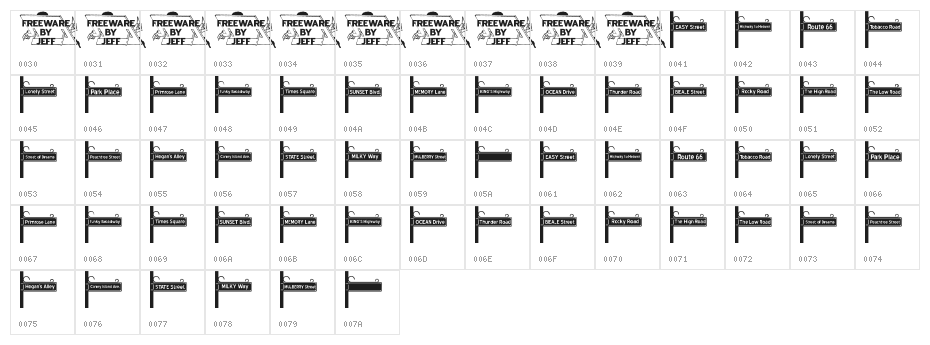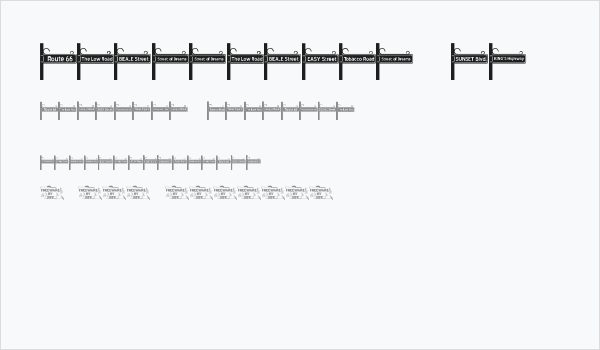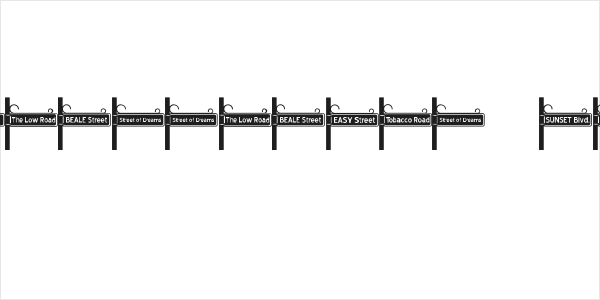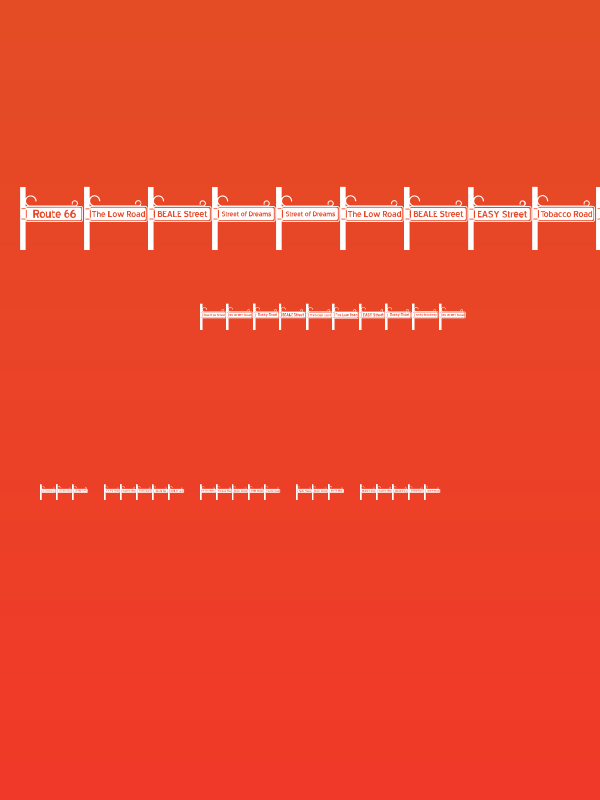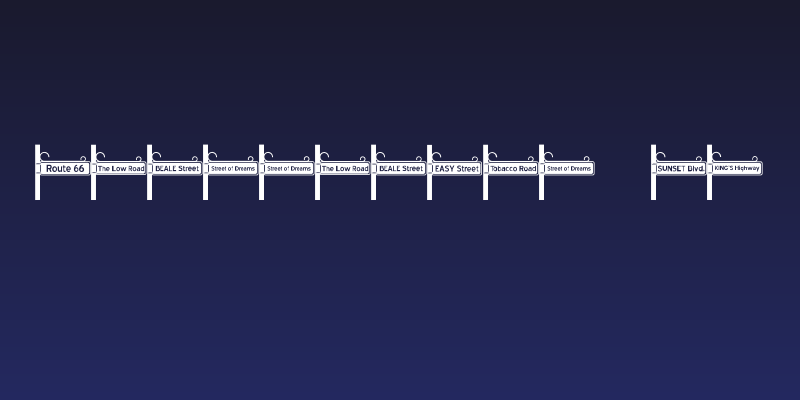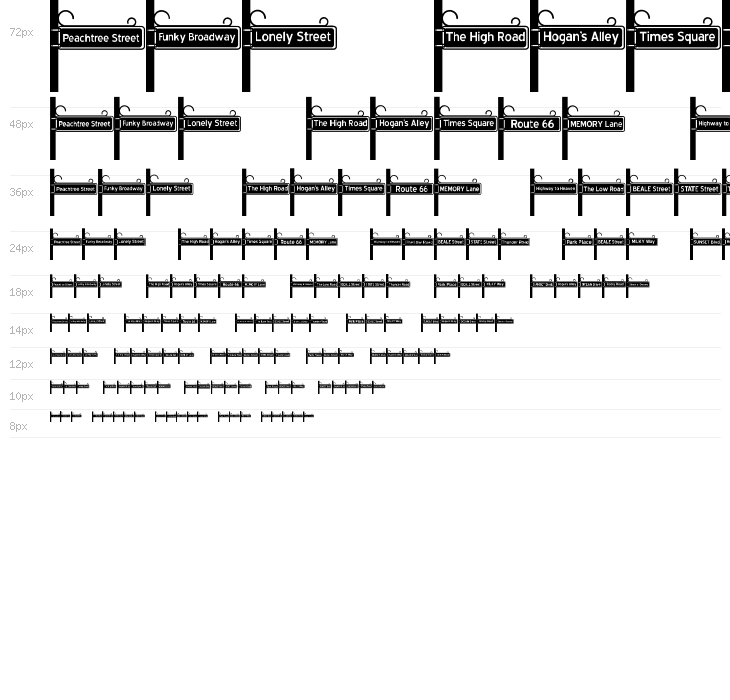
Crossroads JL Font
| Vorgeschlagene Projekte | Ideal for posters, signage, branding projects, and any design work that seeks to capture an urban or playful theme. |